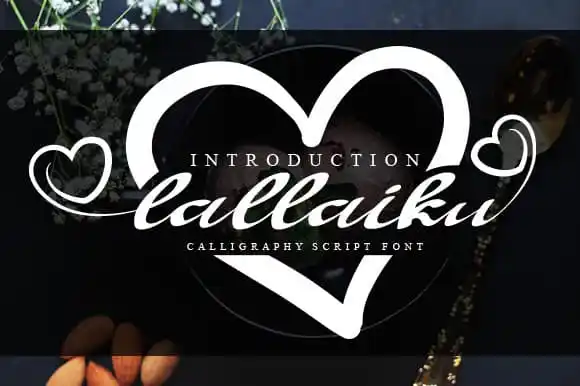
Lallaiku Calligraphy Font
A Lallaiku Calligraphy Font é uma opção perfeita para aqueles que buscam adicionar um toque autêntico a seus projetos digitais e impressos, destacando-se em estilos de escrita elegantes. Este design moderno se adapta a diversos usos, desde arranjos de paredes e invitações de casamento até logomarcas para redes sociais, publicidade, embalagens, identidade visual, fotografias e até mesmo marca d’água. Com sua estrutura arquitetônica fluida, esta fonte é ideal para criar um design impecável. Seu charme e elegância se combinam perfeitamente com qualquer projeto que exige uma escrita de qualidade, tornando-a uma escolha inteligente tanto em produtos comerciais quanto em projetos pessoais. Ideal para quem procura aperfeiçoar sua identidade visual ou deseja dar um toque singular aos seus projetos digitais e impressos, a Lallaiku Calligraphy Font é uma fonte chamativa que certamente não decepcionará.